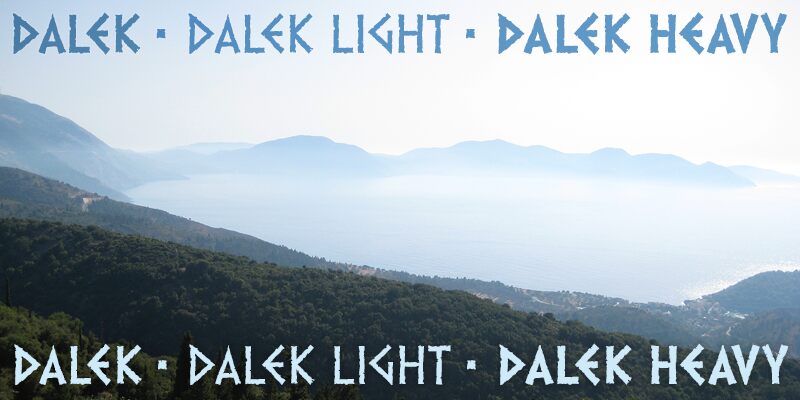
Il font Dalek di Keith Bates è un carattere display gratuito dallo stile vissuto, che sembra inciso nel metallo da una macchina antica e ostile. Le sue maiuscole frastagliate, i bordi irregolari e le influenze degli alfabeti greco, fenicio e runico donano a ogni parola un'energia sci-fi ruvida – a metà tra un fumetto vintage e un avvertimento alieno. Le lettere sembrano scavate nell'inchiostro, con un ritmo sufficiente a restare leggibili pur mantenendo un aspetto meravigliosamente instabile.
Con Dalek, puoi dare all'istante ai tuoi poster sci-fi, titoli di fumetti, zine retrò, loghi di giochi, volantini e merchandising un tocco grezzo in stile TV21. Questo font gratuito dà il meglio di sé alle grandi dimensioni, dove la sua texture erosa può davvero incidere la pagina o lo schermo; abbinalo a un sans serif pulito per i testi di supporto per garantire la leggibilità mentre Dalek fa il lavoro sporco.